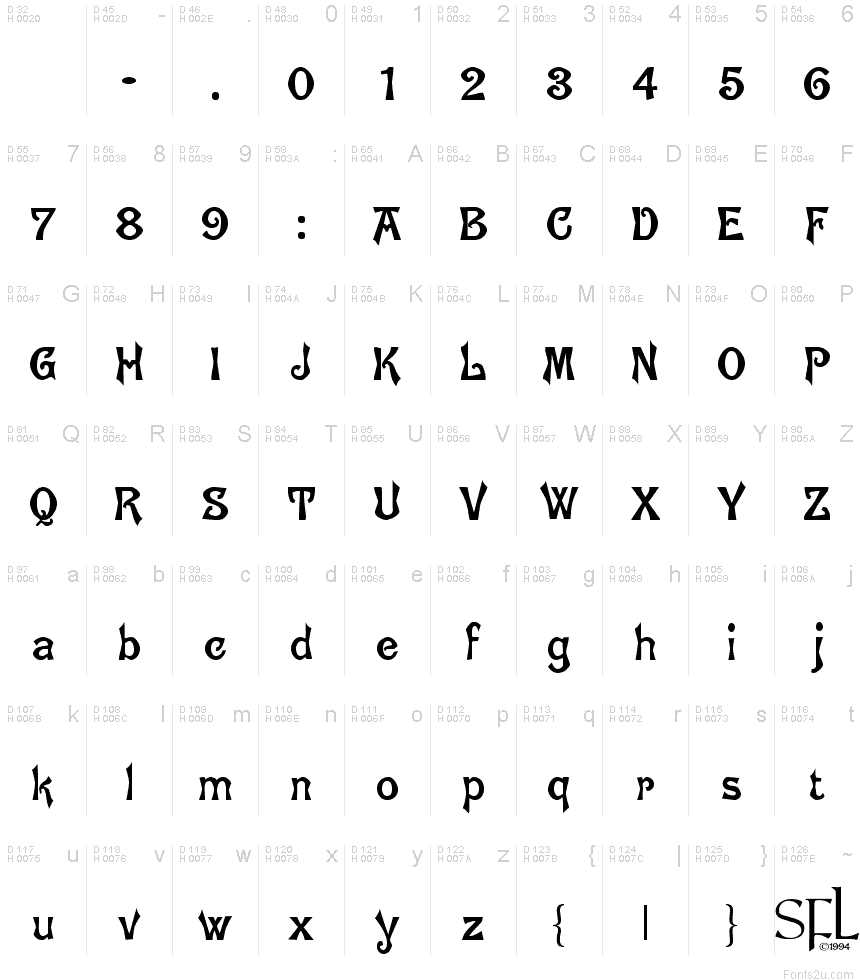
خط Bruges من تصميم David F. Nalle هو خط عرض مجاني بنمط ريترو (كلاسيكي)، يمنحك شعوراً بعناوين حيوية مكتوبة يدوياً على ملصق قديم. تتميز الخطوط بسمكها وأطرافها المستديرة التي تتذبذب قليلاً، مما يضفي على كل كلمة إيقاعاً ناعماً ومرحاً، في حين تمنحها نقاط الدخول الحادة لمسة من الجرأة المناسبة. يبدو الخط ملموساً ومشاكساً بعض الشيء، وكأنه يجمع بين لافتات الكرنفالات الكلاسيكية وشعارات كتب الحكايات الخيالية.
باستخدام Bruges، ستكتسب عناوينك فوراً صوتاً جريئاً ومسرحياً يجذب الانتباه على الملصقات، وأغلفة الكتب، وألعاب الفانتازيا أو القرون الوسطى، وتصاميم المهرجانات، ولوحات الطباشير في المقاهي. يتألق هذا الخط المجاني عند استخدامه بأحجام كبيرة؛ لذا ننصح بإقرانه بخط بلا زوائد (Sans Serif) بسيط للنص الأساسي للحفاظ على توازن التصميم وسهولة قراءته.